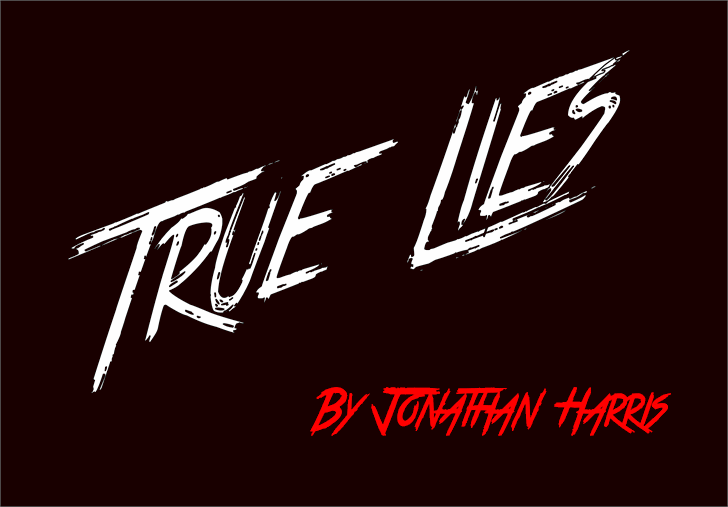
A True Lies é uma fonte script criada por Hamilton que oferece um estilo elegante e sofisticado. Suas letras são perfeitamente adaptadas para textos em cartões de agradecimento, listas de presentes ou qualquer aplicação em que você deseje dar aos leitores uma impressão memorable. A True Lies é uma fonte que evoca as nuances do melhor papel-dourado e o encanto dos tempos mais bonitos. Se procura um estilo elegante que se destaca da multidão, esta fonte script é a escolha perfeita para o seu projeto. Para quem deseja usar essa fonte em uma aplicação comercial, é essencial comprar um licenciamento no site do fabricante e está disponível também diretamente por email. A verdadeira elegância começa com uma boa escrita. Experimente True Lies hoje mesmo.